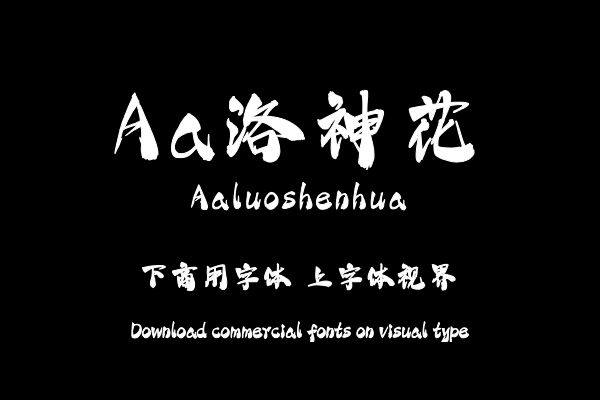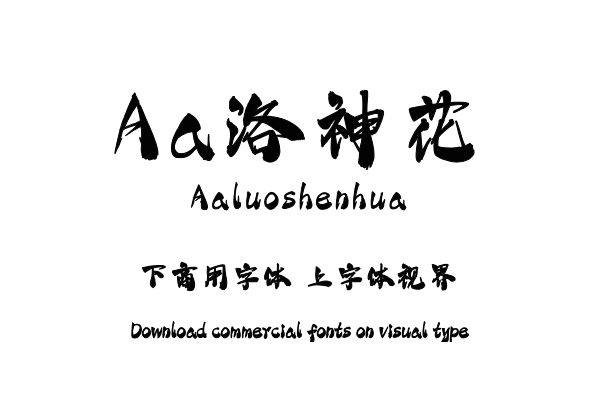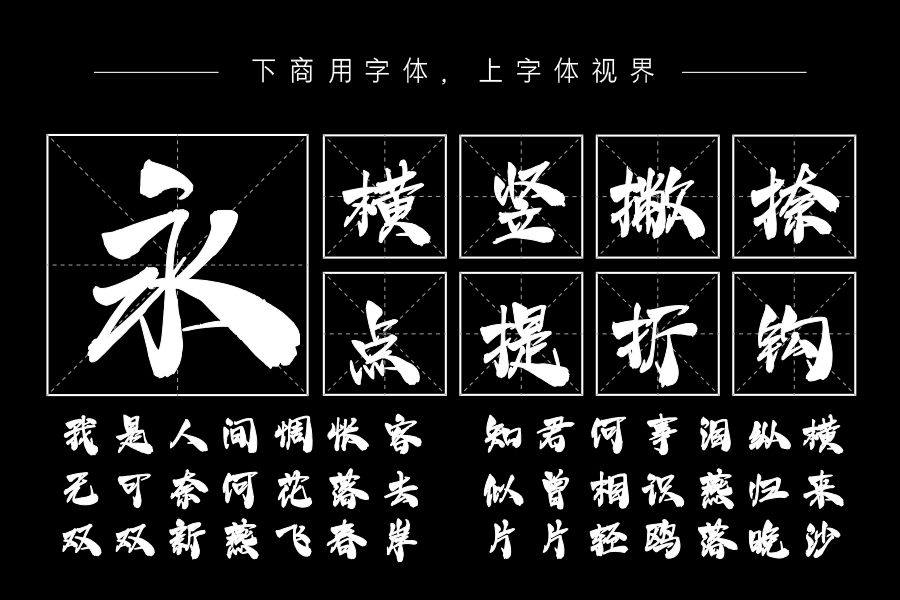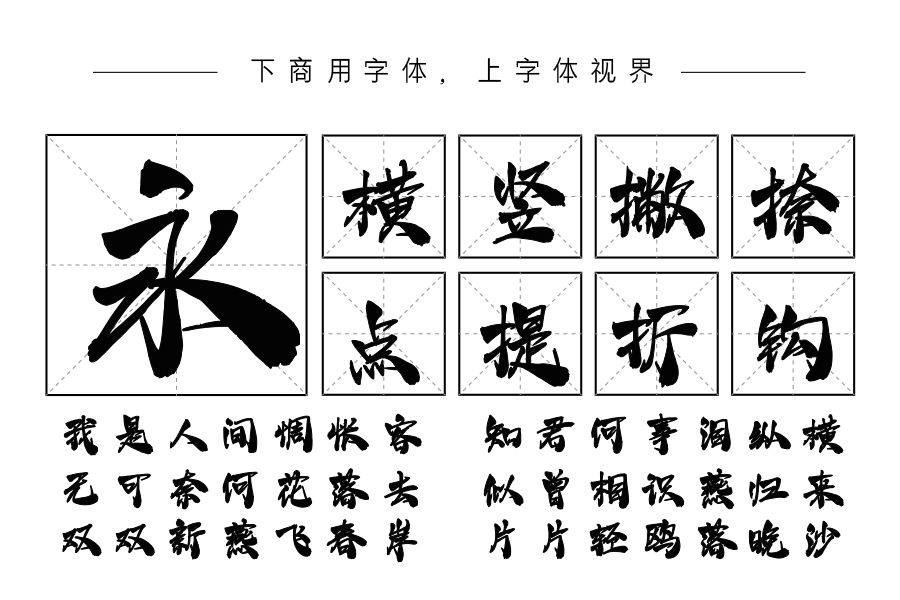
通过圆润用笔显出饱满爽朗之气,或粗或细,随态运奇。由细渐粗,仿佛旭日东升,草木方萌,一派生机盎然,欣欣向荣的气象。购买须知:“下载服务费”与“字体VIP”所获得字体 仅用于个人非商用, 商用请联系付费授权。本字体为电脑用字,手机没有root权限不支持直接手机换字(手机如何root,请自行百度搜索教程)。购买前请先 了解清楚后再付款 ,字体为虚拟产品无法回收 一旦购买不支持退款。